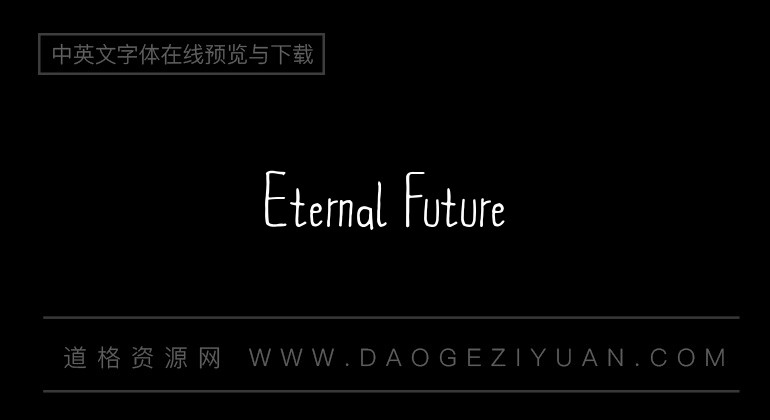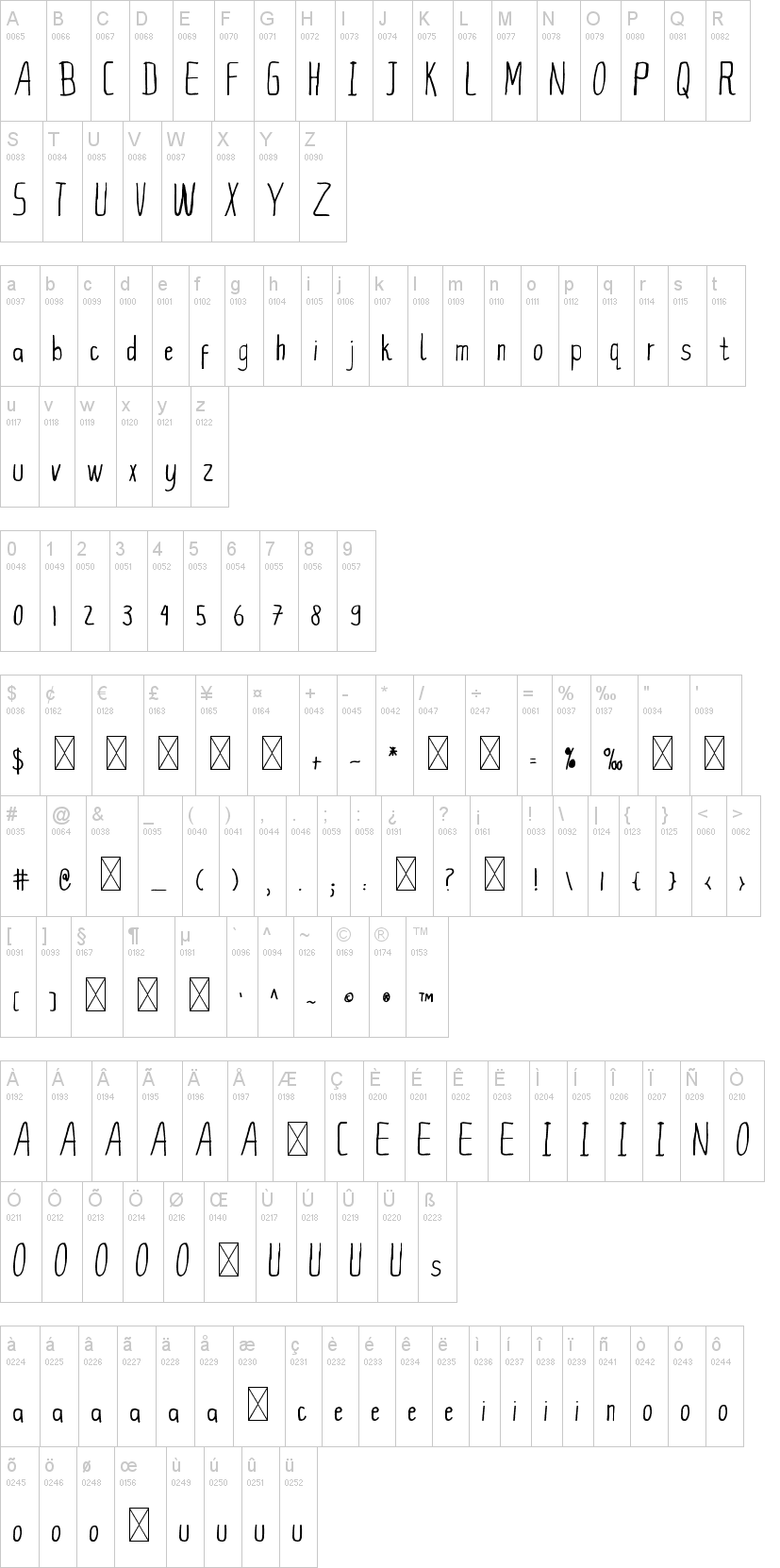
Eternal Future
Eternal Future 字体是一款美观大方的新型字体,它的特点是使用平滑的曲线,给人以现代感的视觉效果,而不是传统的粗体或细体字体。它的最大特点是它的字符拥有良好的空间分布,使字体看起来更加简洁。它也具有良好的可读性,使得文本更加清晰,更易于阅读。此外,它还具有良好的多语言支持,可以支持多种语言的文本。
Eternal Future是一款非常不错的手写艺术字体,具有很好的视觉感,适合于文化类的宣传设计、商业类品牌的广告和产品包装设计以及个性化文字排版等较多场景。
Eternal Future字符映射图